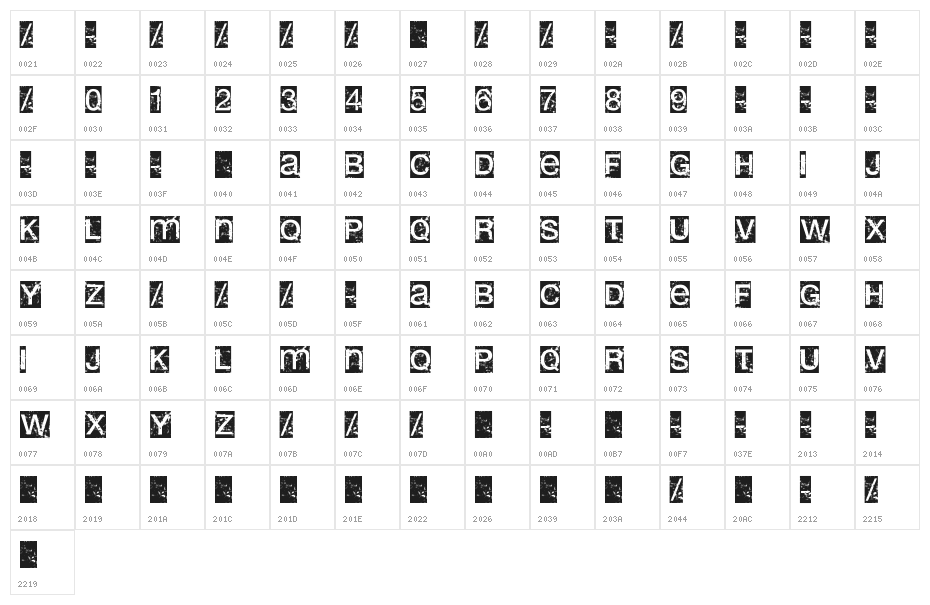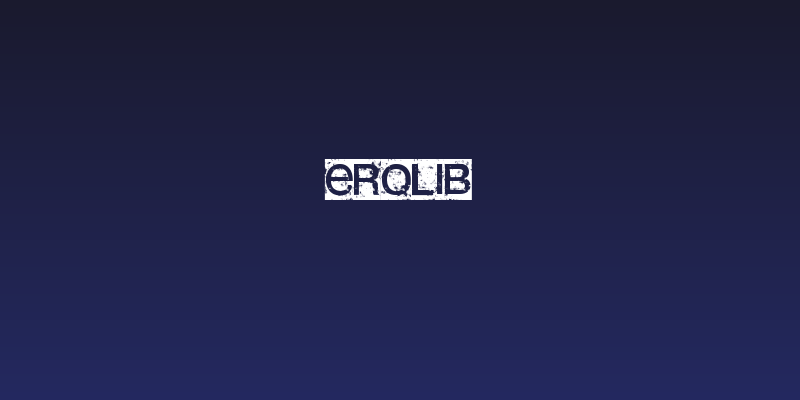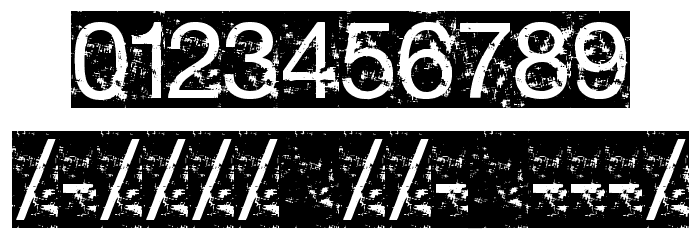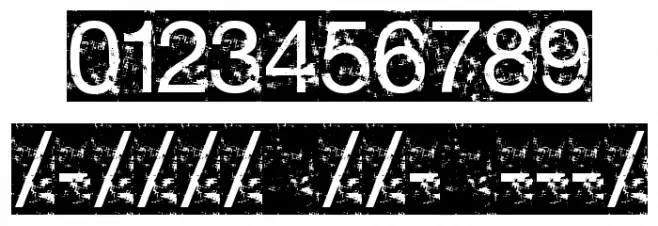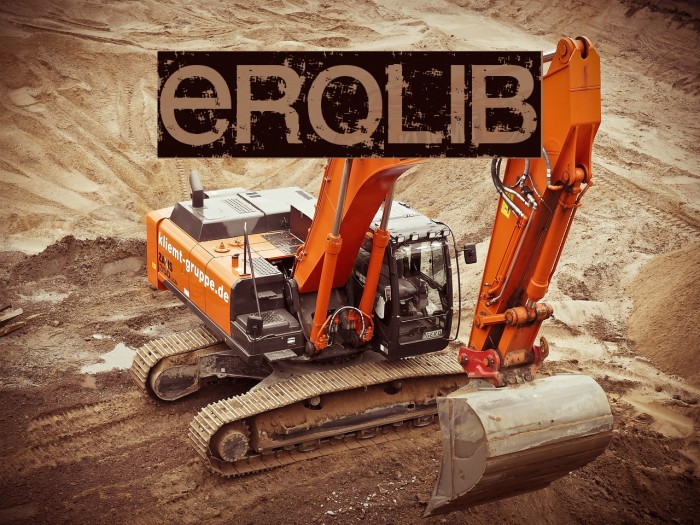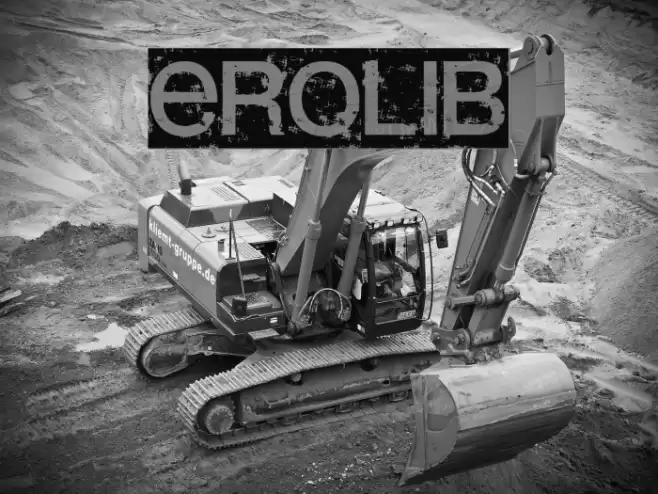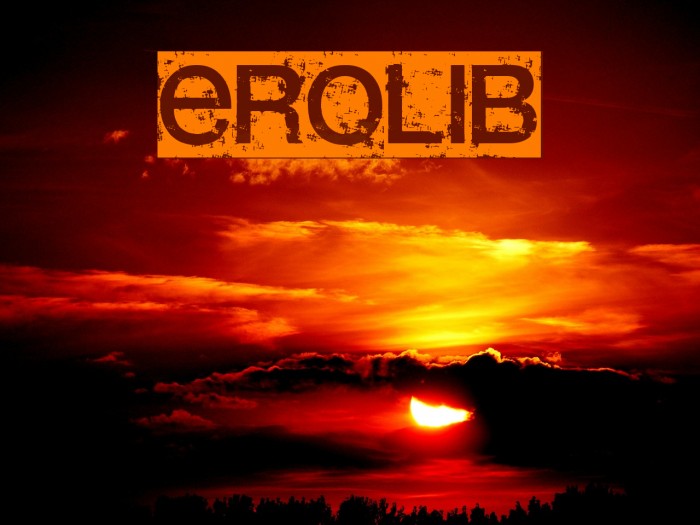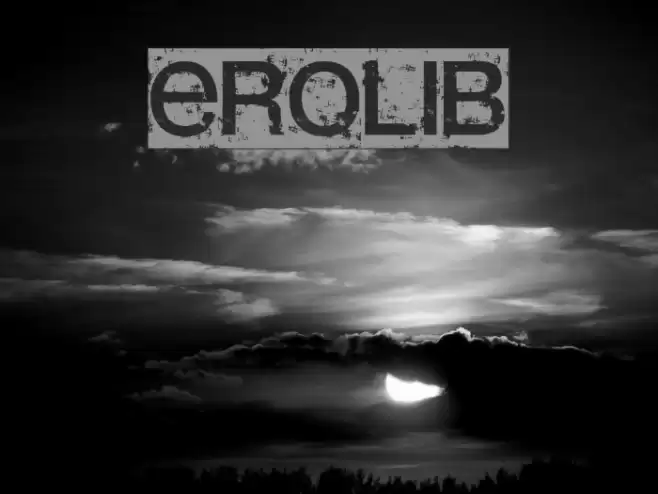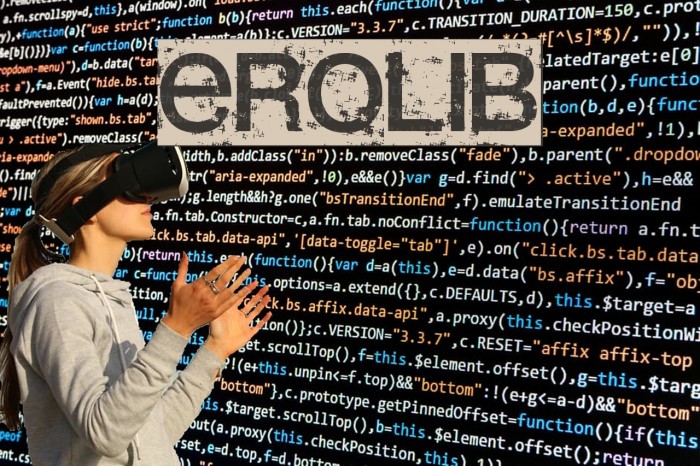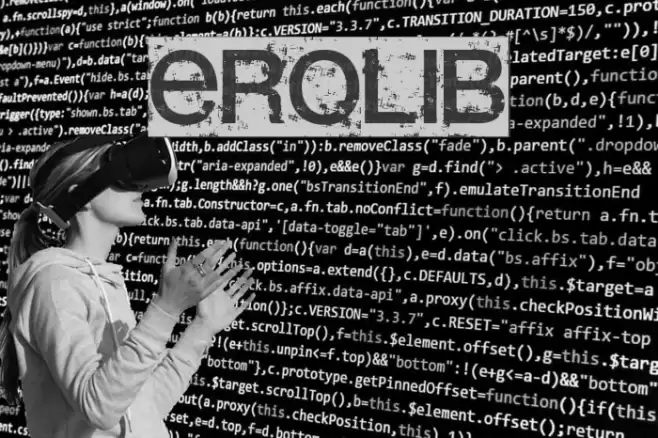
erolib Font
✎ Distorted Eroded
| Progetti proposti | Ideal for album covers, posters, branding for edgy or vintage-themed products, and any design requiring a bold, textured look. |